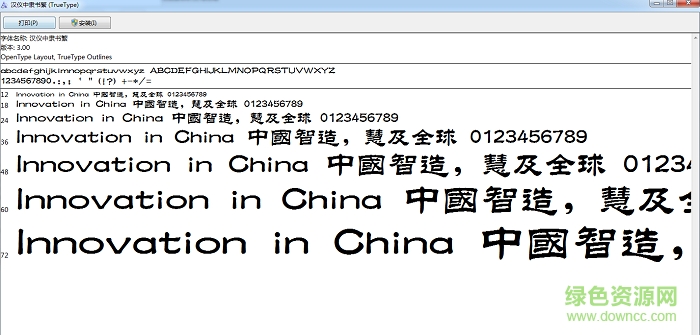
hyf3gf字體(漢儀中隸書繁)是一款繁體的隸書字體,該字體結(jié)構(gòu)嚴(yán)謹(jǐn),字形優(yōu)美,字面扁而寬,給人一種穩(wěn)重沉著的感覺,歡迎大家免費(fèi)下載這款繁體字體!
隸書的結(jié)構(gòu)特點(diǎn)
變畫為點(diǎn)變連為斷
我們知道篆字不用點(diǎn),即使用點(diǎn)也只是一種渾圓點(diǎn)。而隸書中點(diǎn)已獨(dú)立了出來(lái),不再依附于畫,而且點(diǎn)法也日益豐富,有平點(diǎn)、豎點(diǎn)、左右點(diǎn)、三連點(diǎn)(水旁)、四連點(diǎn)(火旁)等等。
字形扁方左右分展
隸字一反篆字縱向取勢(shì)的常態(tài),而改以橫向(左右)取勢(shì),造成字形尚扁方,筆畫收縮縱向筆勢(shì)而強(qiáng)化橫向分展。
強(qiáng)化提按粗細(xì)變化
寫篆書時(shí)用筆的縱向提按要求不現(xiàn)痕跡,而隸書則有意強(qiáng)調(diào)提按動(dòng)作,形成筆畫軌跡顯著的粗細(xì)、轉(zhuǎn)承變化,起、行、收用筆的三過(guò)程都有了明確的體現(xiàn)。這與后來(lái)的楷書已很相近。
化圓為方化弧為直
這是隸書簡(jiǎn)化篆書的兩條基本路子。不過(guò)如果不了解篆書的圓,就不易掌握好隸書的方。因?yàn)殡`筆中的直畫或方折,還無(wú)不包藏著篆字的弧勢(shì),所以隸筆的直往往有明顯的波動(dòng)性,富于生命力。
起筆蠶頭收筆雁尾
這是隸書用筆上的典型特征,特別是隸字中的主筆橫、捺畫幾乎都用此法。所謂“起筆蠶頭”,即在起筆藏(逆)鋒的用筆過(guò)程中,同時(shí)將起筆過(guò)程所形成的筆畫外形寫成一種近似蠶頭的形狀?!笆展P雁尾”,即在收筆處按筆后向右上方斜向挑筆出鋒。